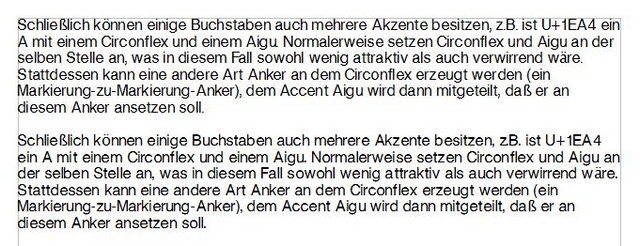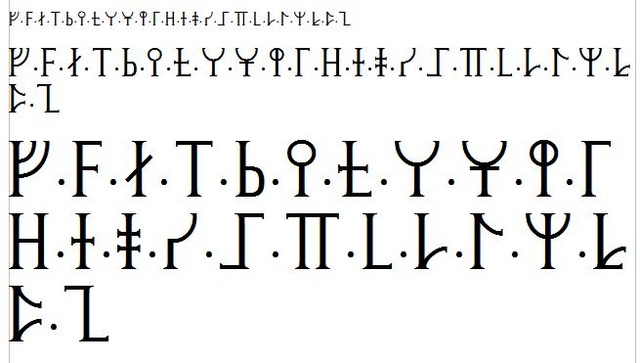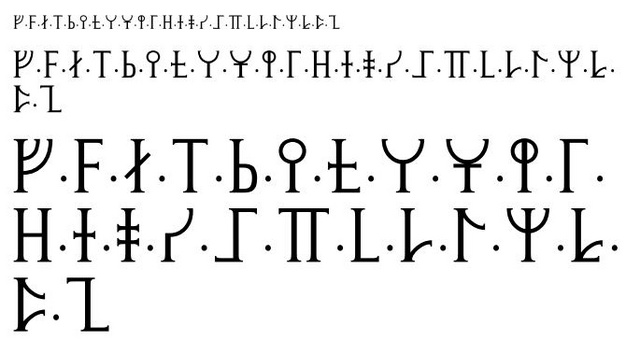
Unharmonisches Erscheinungsbild am Bildschirm; Editor: FontForge
ich - absoluter Laie - habe ein Problem mit FontForge;
zwecks Lerneffekt im Umgang mit den Optionen kopierte ich die Grundzeichen eines freien serifenlosen Fonts in eine neue Datei.
Dabei stellte ich fest, dass jedoch die Erscheinung am Computer unterschiedlich ausfällt (z.B. in OpenOffice);
Unter "Element > Schrifteigenschaften" hatte ich schon alle möglichen Werte verglichen und der Originaldatei angepasst;
kann also nicht daran liegen. (?)
Das Problem ist die unausgeglichene Erscheinung: Die Verhältnisse der Größen untereinander (z.B. von Zweigen) einer Glyphe am Bildschirm entsprechen nicht den tatsächlichen Verhältnissen in der Vektorgrafik.
Im Druck (bzw. als PDF) sind die Verhältnisse völlig normal, entsprechen dem Originalfont bzw. den Vektorgrafiken.
(Könnte ja aus diesem Grund mir egal sein,... nur ich möchte eine Runen-Schrift erstellen, die auch am Bildschirm sehr gut aussieht/ zu lesen ist).
im Bild: Unten meine Kopie; oben das Original.
Das Problem lässt sich in einem Wort zusammenfassen: Hinting!
Eine »Lösung« jedoch nicht. Es gibt manuelles Hinting, dass Standard-Fonteditoren überhaupt nicht verarbeiten können. Ein Öffnen-Ändern-Abspeichern wie bei bei Word und Co. ist dann schlicht unmöglich.
Es gibt auch verschiedene Formen des Auto-Hintings, die wiederum von verschiedensten Einstellungen abhängen. Aber das ist auch ein komplexes Thema …
danke für deine Antwort; also muss ich mit dem Schaden leben?
Ich hatte nun in Fontforge das "Auto-Hinten"- probiert, aber eine Besserung konnte ich nicht erkennen.
meinst du, ich solle das "hinting" für jedes zeichen einzeln anfertigen?
ich hatte schon meine ersten eigenen Kreationen erstellelt, mit "Füßchen" :-) (find ich optisch schöner)
anbei zwei kleine Bilder; das eine die Ansicht am Bildschirm, zweite als Druck.
Ich hatte auch schon mal einen realen Ausdruck gewagt und war eigentlich zufrieden;
außer die Zweige, vor allem die geraden/ waagerechten, die sind mir doch zu dünn;
die "runden" Zweige sind zwar am Bildschirm förmlich zu sehen, aber irgendwie auch viel zu zart,... also anstrengend zu erkennen.
War jetzt auch nicht sooo schwer/ zeitintensiv, darum überlege ich, die Zeichen nochmal neu zu erstelle und allg. fetter.
?
(Hatte auch überlegt, ohne Serifen; jedoch geben gerade diese irgendwie den gewissen Reiz; ?)
bei den Bilder sind folgende Schriftgrößen:
1. Reihe -> 12
2. ... -> 24
3. ... -> 48
Wenn Dir das automatisch erzeugte Hinting für Deine Runenschrift nicht gut genug ist, mußt Du eben von Hand Hinting-Informationen erstellen. Das ist allerdings aufwendig.
Vielleicht hast Du auch das Hinting nicht für alle Zeichen erzeugen lassen? Markiere in Fontforges Zeichenübersicht alle Zeichen (z. B. über Strg + A) und klicke dann im Menü auf Hints/Auto-Hinten. In den Zeichenfenstern solltest Du danach grüne und blaue Flächen sowie grüne Linien sehen.
Weitere Möglichkeit: Wenn du nach einem Autohinting und erneutem Export der Schrift keinerlei Änderung in den Awendungsprogrammen sehen kannst, stelle sicher, dass wirklich die neue Version der Schrift verwendet wird, und nicht noch die alte in irgend einem Cache sitzt.
Die Rundumchlag-Lösung dafür ist, während der Entwicklung vor jedem Export der Schriftfamilie einen neuen Namen zu geben, d.h. die erste Version heißt "Runenschrift-v1", dann "Runenschrift-v2", etc. Dann kann es keine Cacheprobleme geben.
Ich probiere nun, selbst Hinting-Informationen zu erstellen.
Wie mach ich das für Rundungen?
Es gibt einen recht guten Auto-Hinter, der z.B.ö für das Linux Libertine-Projekt auch verwendet wird (Diese Schriften sind ja auch mit Fontforge gestaltet worden). Die Ergebnisse sind damit wirklich recht gut, und in den allermeisten Fällen, wenn man die Schriftart nicht unbedingt als Display-Font einsetzten möchte, sondern mit einer vernünftigen Optik im Editor zufrieden ist: http://www.freetype.org/ttfautohint/